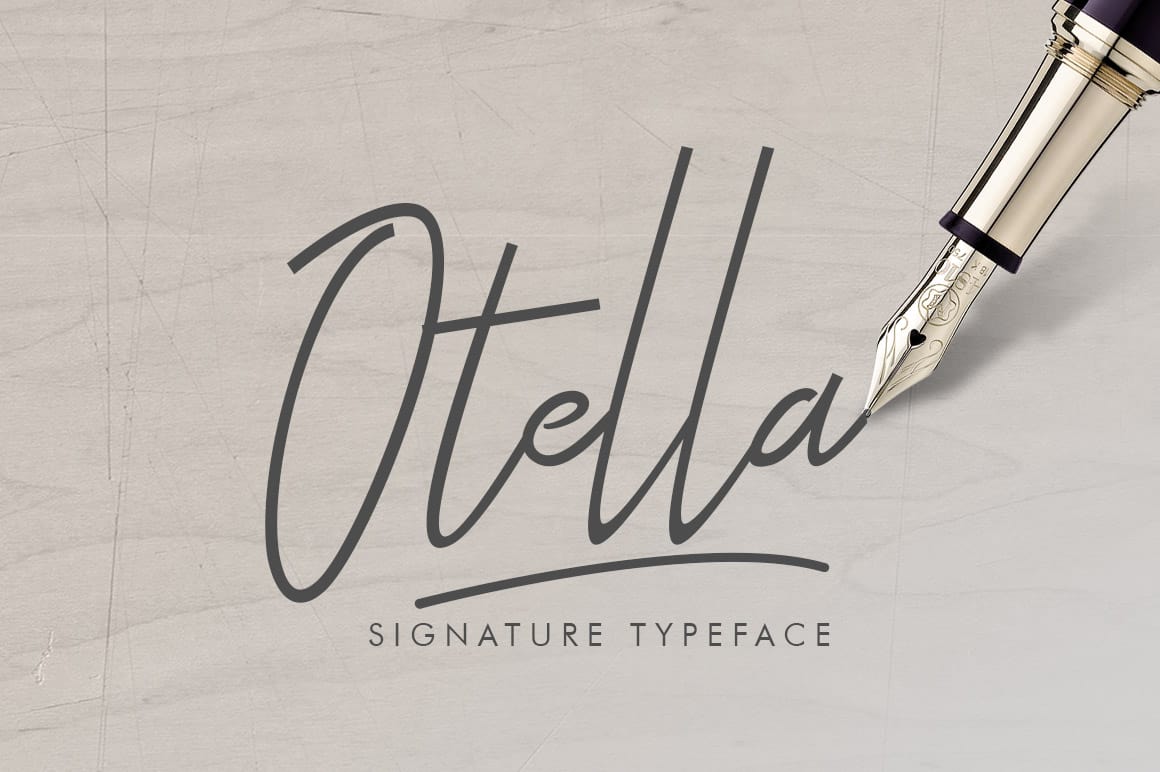
Они позволяют вам сделать индивидуальную печатную продукцию с лучшим фирменным шрифтом по вашему выбору. Ваши клиенты будут хорошо относиться к активам, которые вы разработали сами.
Социальные сети Чтобы контент в социальных сетях произвел впечатление, вам нужно, чтобы ваша аудитория чувствовала, что они взаимодействуют с вами на личном уровне.